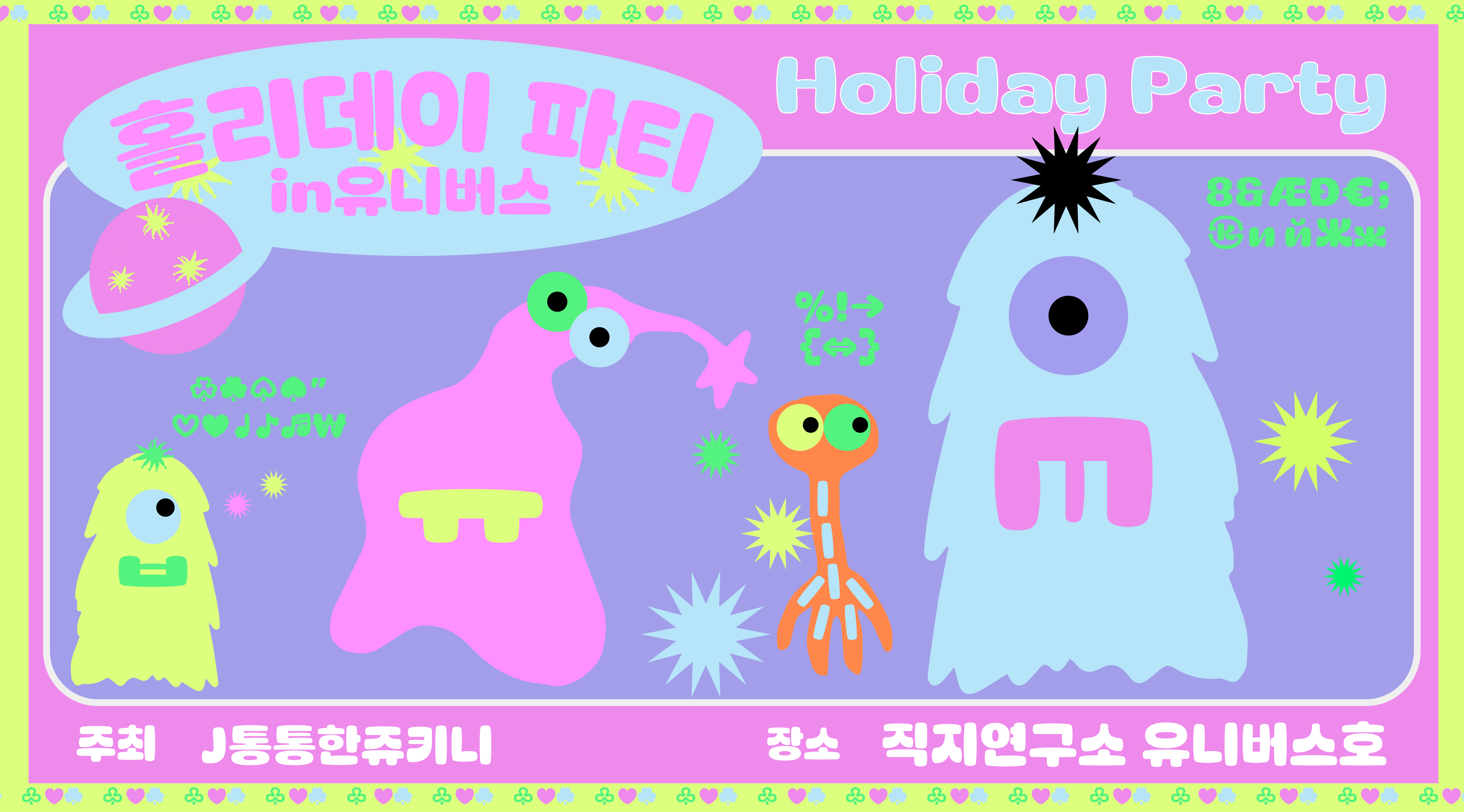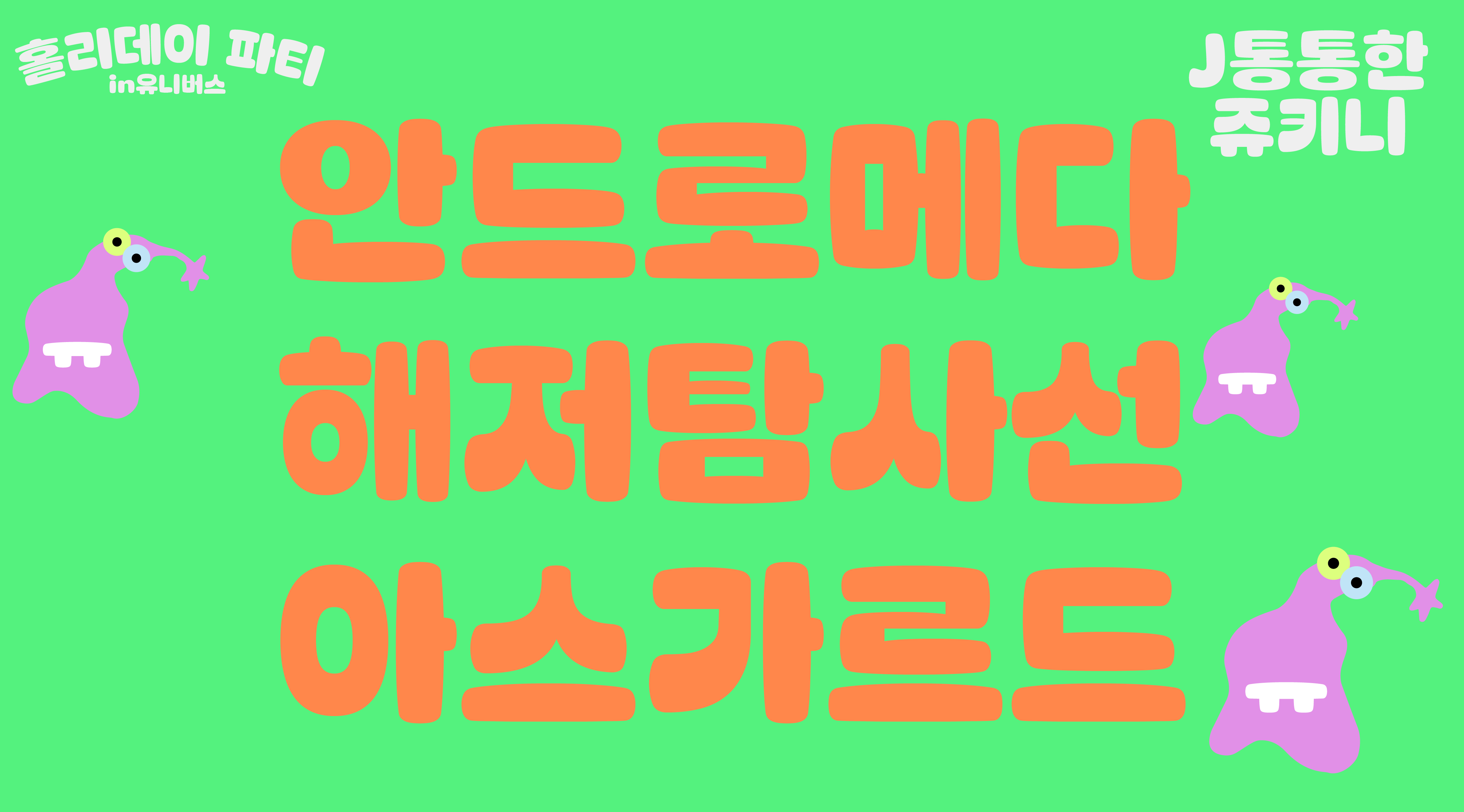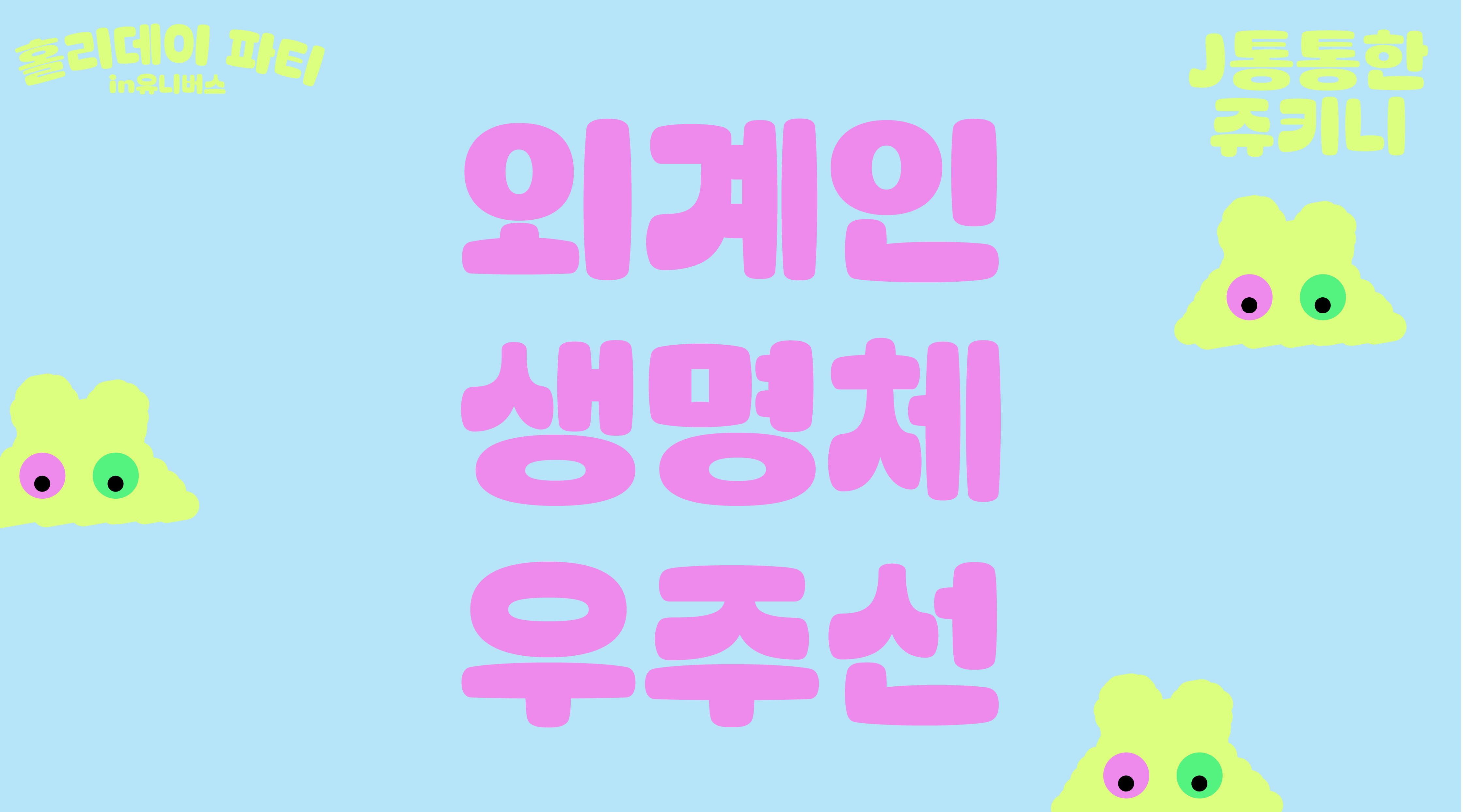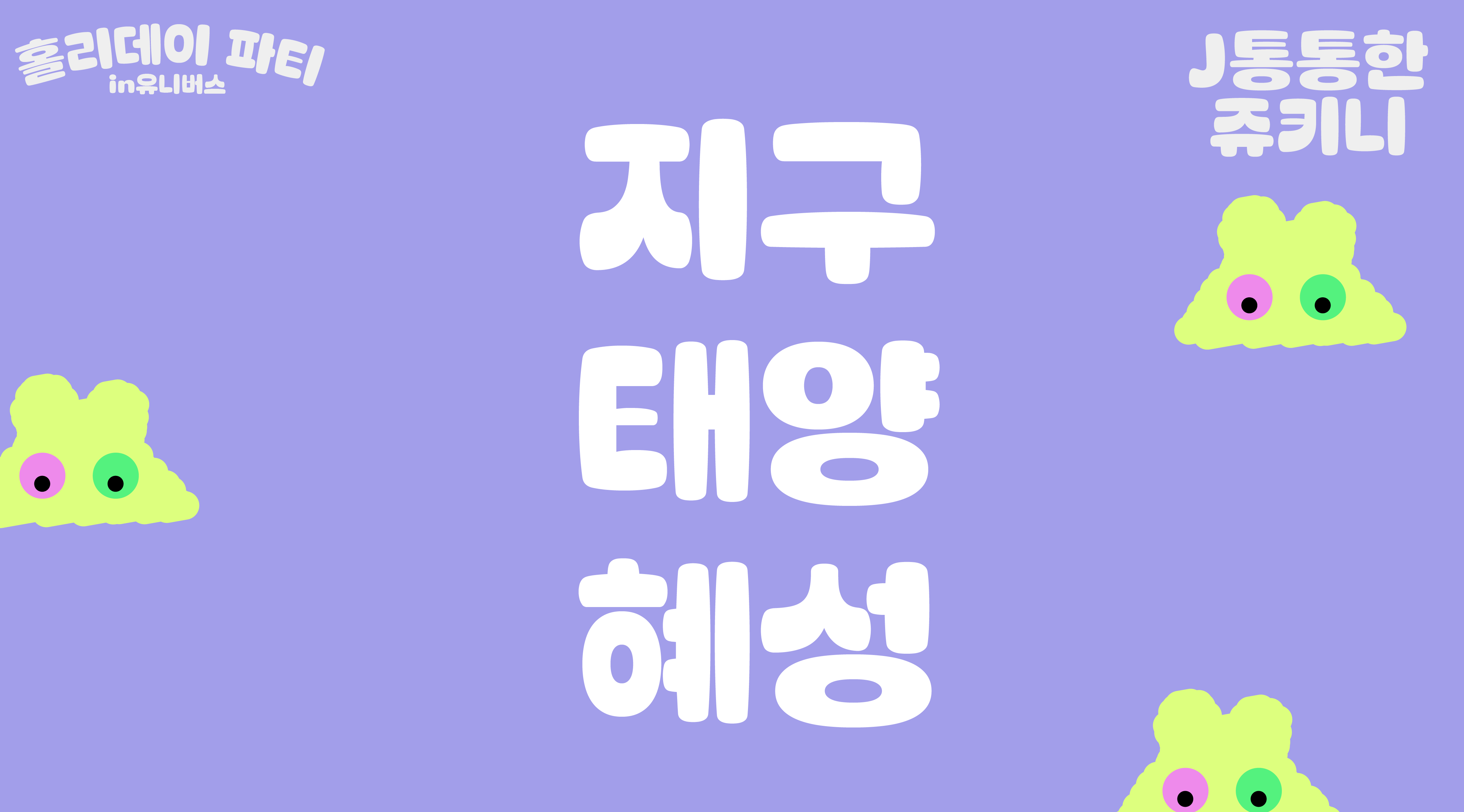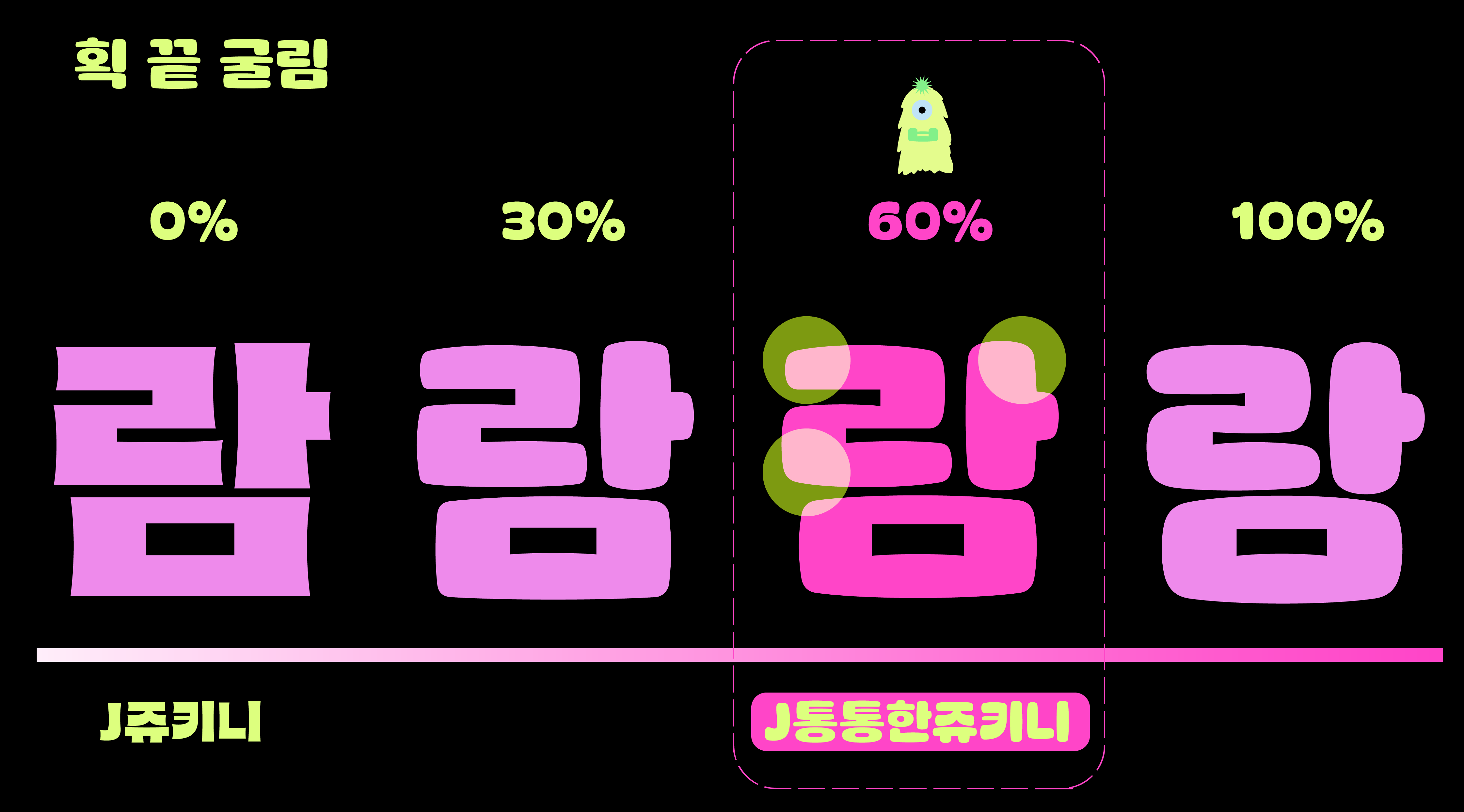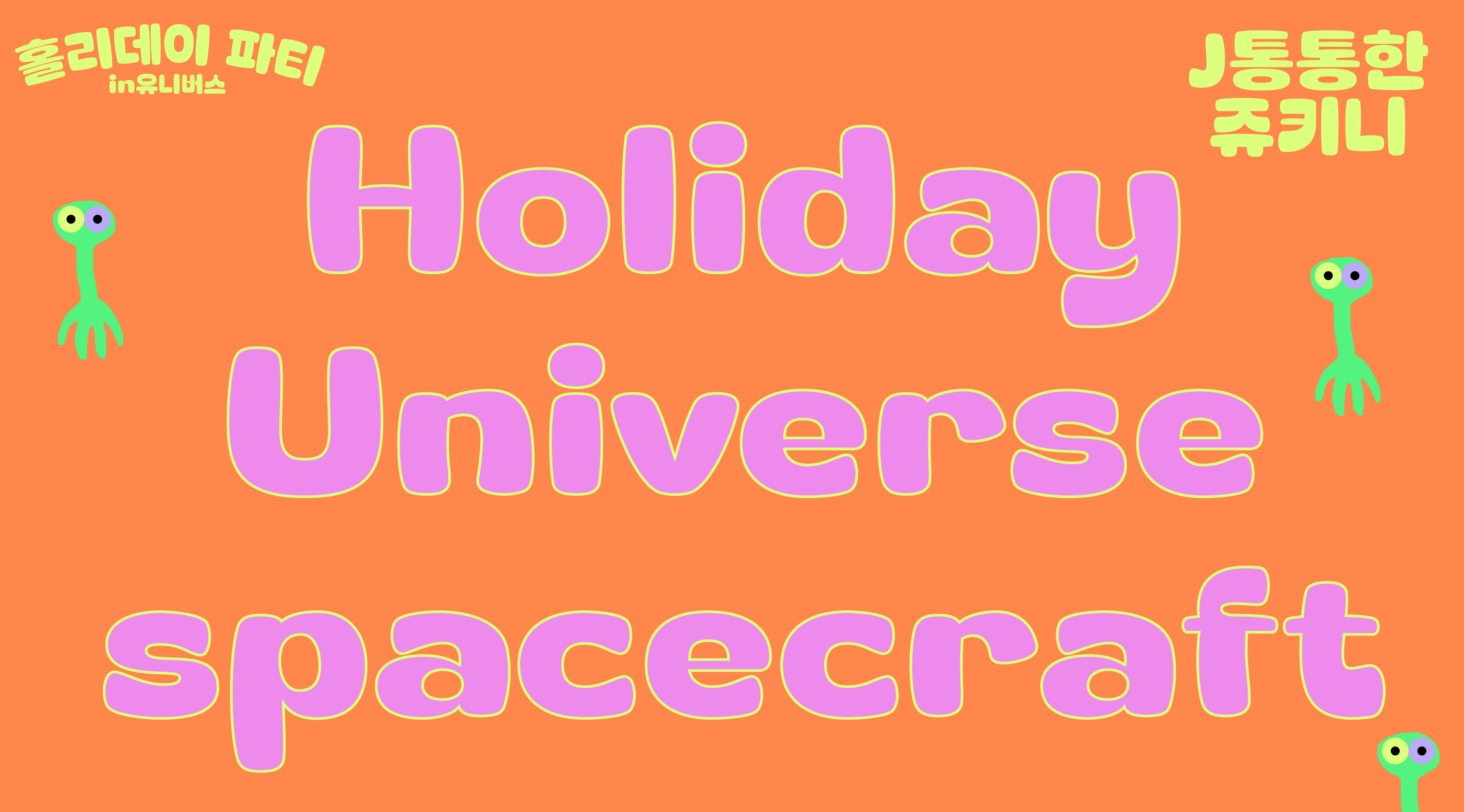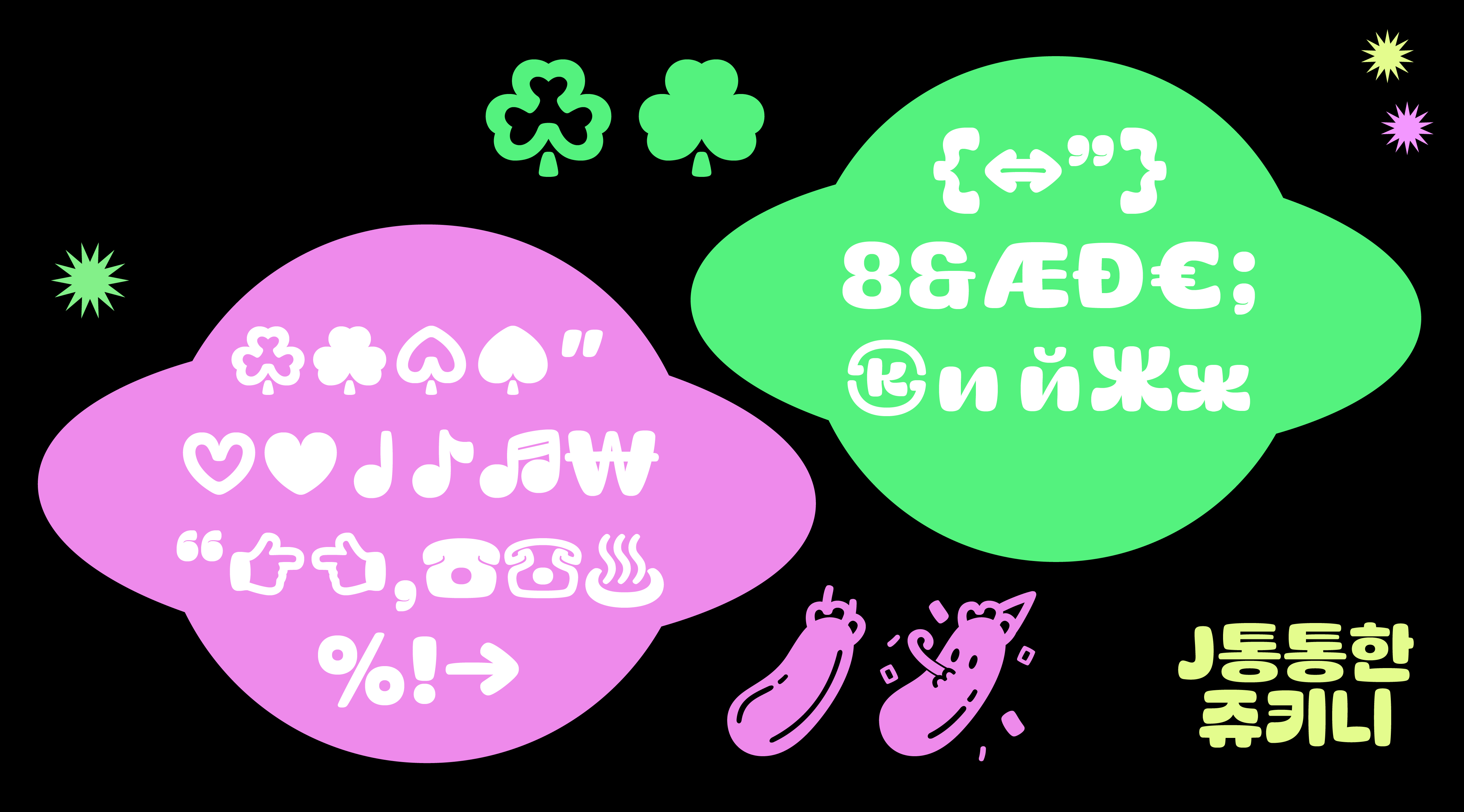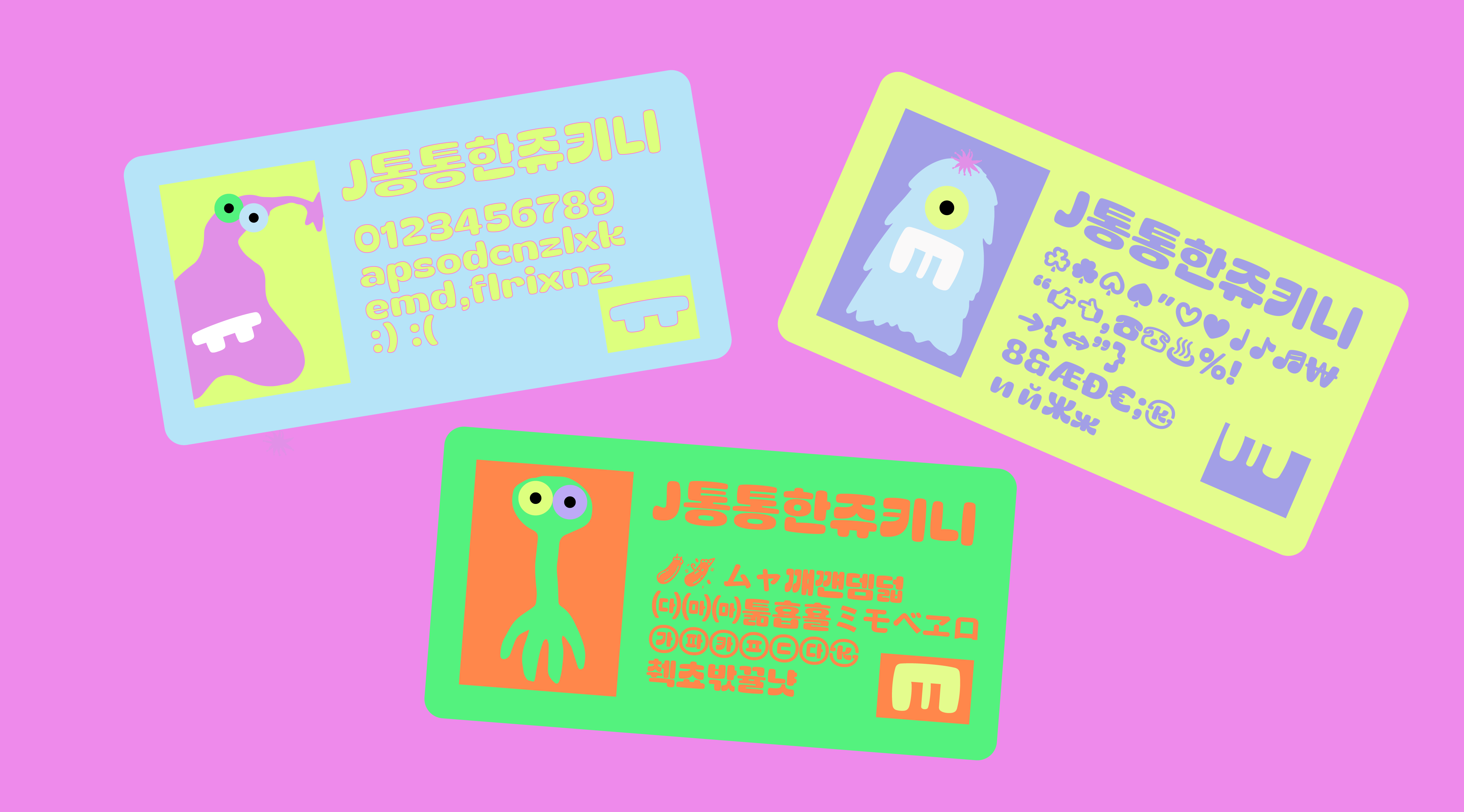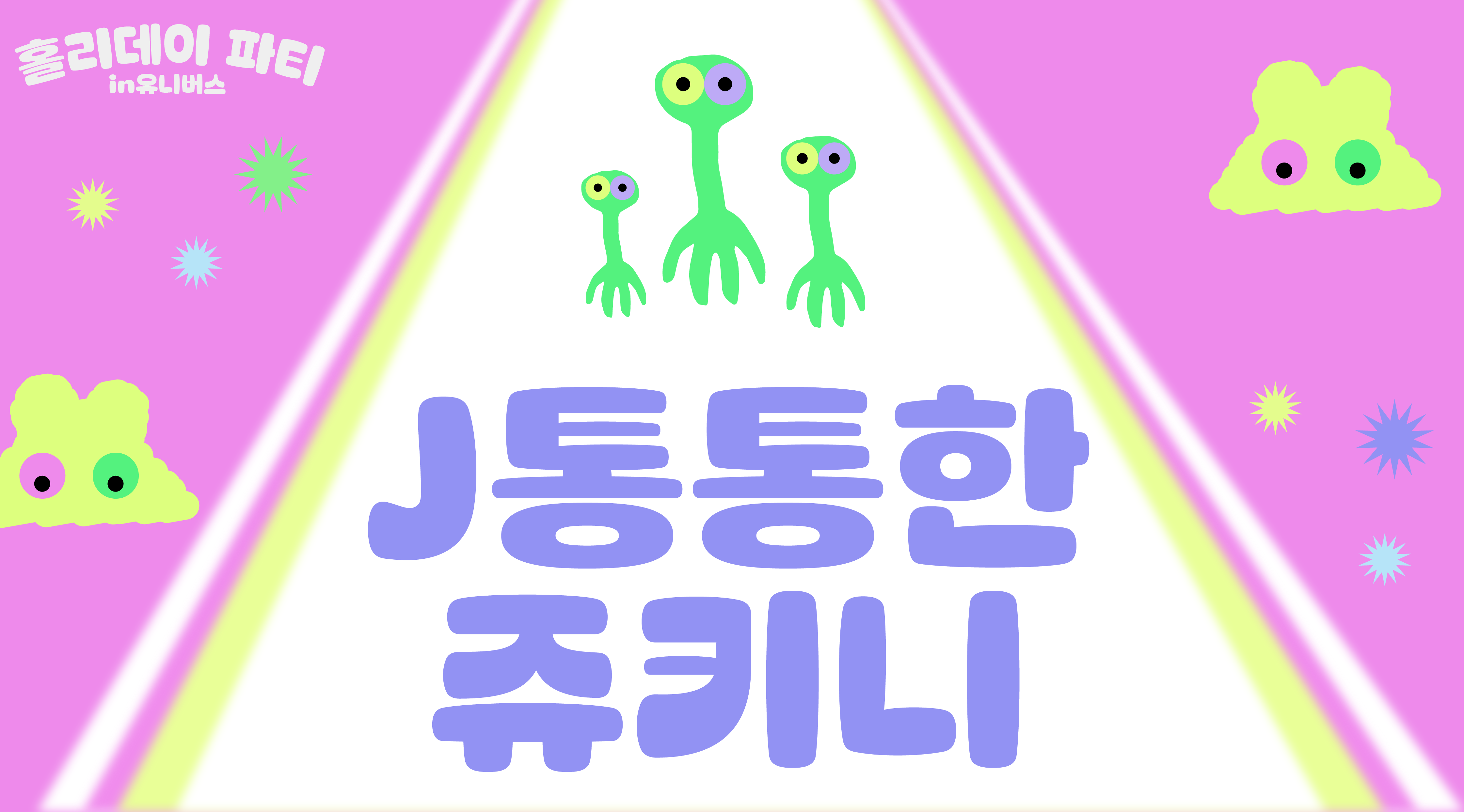
J통통한쥬키니
다양한 컨셉으로 활용이 가능하고 독특한 디자인 요소가 많은 서체 시리즈. 개성있는 디테일로 시각적 재미를 더하고 풍부한 이야기를 담을 수 있는 서체이다.
J통통한 쥬키니는 J쥬키니의 패밀리로 동글동글 귀여운 인상의 타이틀용으로 제작된 서체입니다. 가장 큰 특징이자 차별점은 J쥬키니의 강렬하고 단단한 오목한 획을 반전하여 볼록한 획으로 바꾼 것입니다. 볼록한 특징을 더욱더 강조하기 위해 글자의 모서리 부분에 곡선을 추가하여 J쥬키니와는 상반된 인상을 보여줍니다. 한글 디자인 J쥬키니의 친구답게 같은 뼈대 그리고 획의 강중약 대비, 비대칭적인 ㅅ,ㅈ,ㅊ(ㅆ, ㅉ) 내림, ㅟ 와 ㅝ 의 짧은 기둥에서 보이는 과감한 곡선 획은 유지하면서, 경쾌하면서 단단하고 시원하게 뻗어가는 기존의 J쥬키니와는 다르게 볼록한 획으로 표현되어 오동통하면서 동글동글한 이미지입니다. 디자인하면서 특별히 신경쓴 부분이 있다면 바로 동글동글한 인상에 결정적 역할을 하고 있는 모서리 끝 굴림과 볼록한 획의 연결을 섬세하게 조정하며 작업했습니다. 영문 디자인 한글 디자인의 인상에 맞춰 디자인한 영문 디자인은 J쥬키니의 과감하고 시원한 곡선의 특징을 K, Q , R 에 적용하고 강중약 대비를 살려 한글과 통일성을 가져갔습니다. 한글의 귀여운 인상이 반영된 대문자 G, J, P, R 과 소문자 e, f, g, t, y의 형태를 주목해 주세요. 특문 디자인 귀여운 인상에 딱 어울리는 흥미로운 특수문자가 많습니다. 그중에서도 추가 글립을 제공하는 글립 Club 과 Slash을 소개합니다. - Club(♧, ♣): 행복을 부르는 세잎클로버와 같은 디자인의 특수문자 club(♧, ♣)가 기본 형태 club 뿐만 아니라 추가로 선택이 가능합니다. (J통통한쥬키니를 쓰시는 분들 다 행복만 가득하세요!) - Slash (/) : 굵기가 다른 Slash 두 개가 있으니 용도에 따라 선택, 사용해 주세요. 이 외에도 사랑스러운 특수문자들 ♧ ♣ ♤ ♠ ″♡ ♥♩♪♬\ “☞☜ , ☎ ☏♨%!→{⇔” } 8&ÆÐ€;㉿ийЖж 이 있습니다. 선물 꾸러미와 같은 특수문자를 확인해 보세요! 오픈타입 피처 J통통한쥬키니의 인상에 개성을 더하고 싶은 의도로 숨겨진 일러스트가 있습니다. 궁금하시다면 ^C, ^Z 를 한번 써보세요. (ChubbyZukinie의 대문자 C 와 Z로 기억해 주세요!)